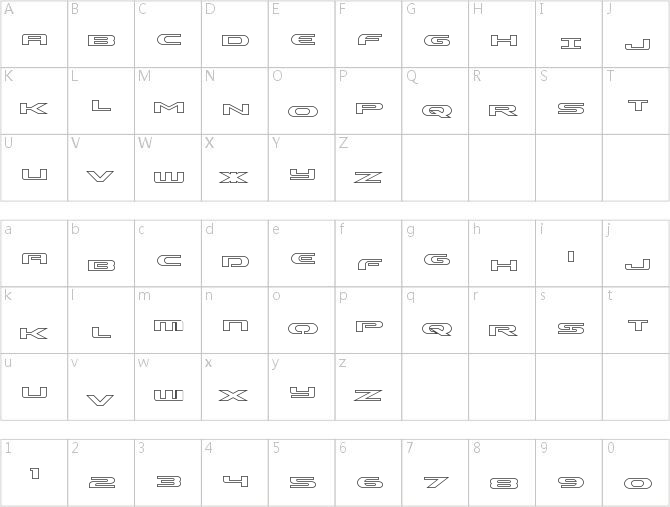
Alpha Men Outline
Alpha Men Outline字體字庫(kù)是一款讓人賞心悅目、百看不厭的英文字體,適合各類(lèi)廣告和產(chǎn)品包裝設(shè)計(jì)應(yīng)用,字體大小0.04MB,格式為ttf字體,上傳用戶(hù)是那是不變的,作者/版權(quán)方為未知